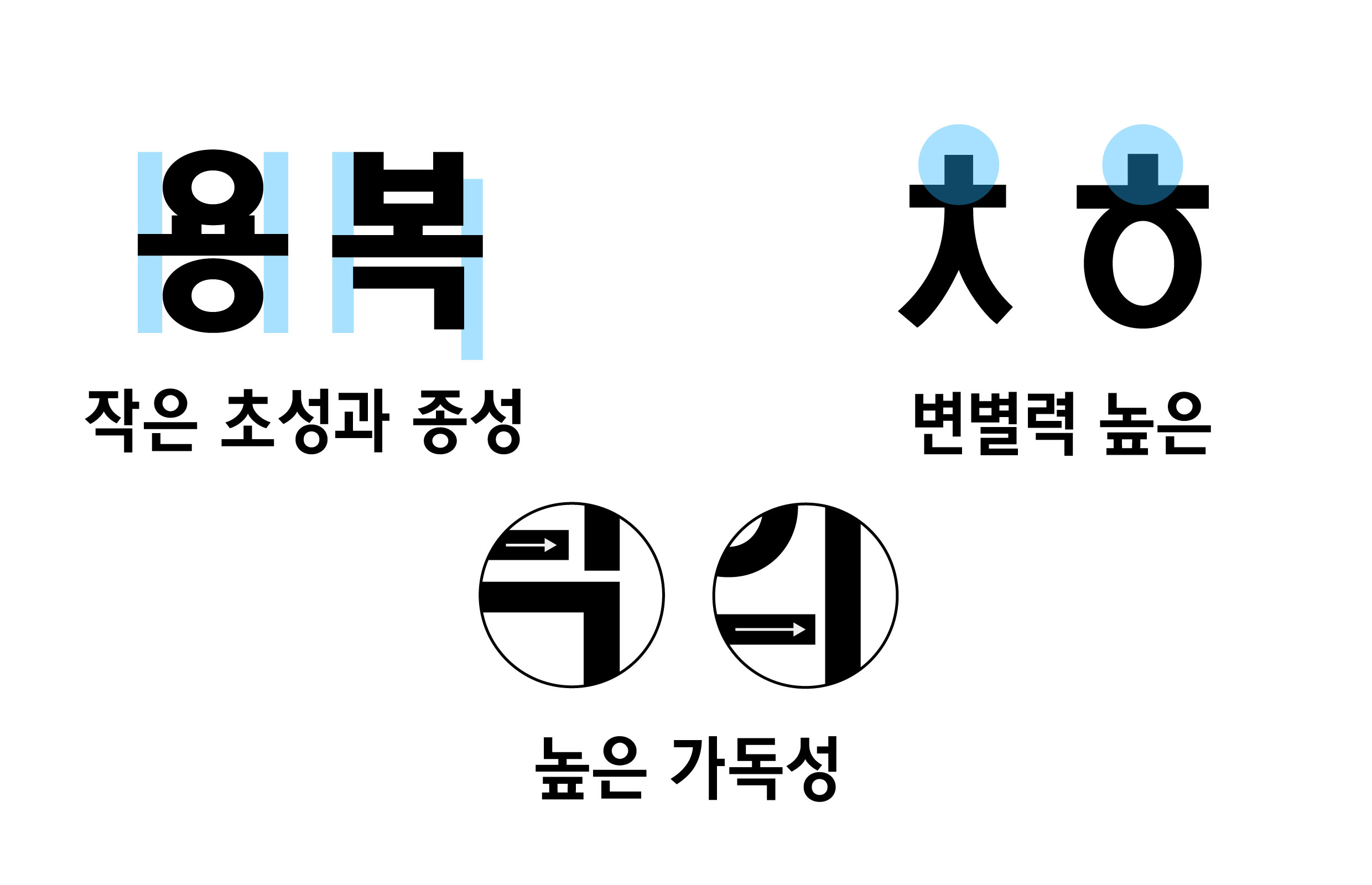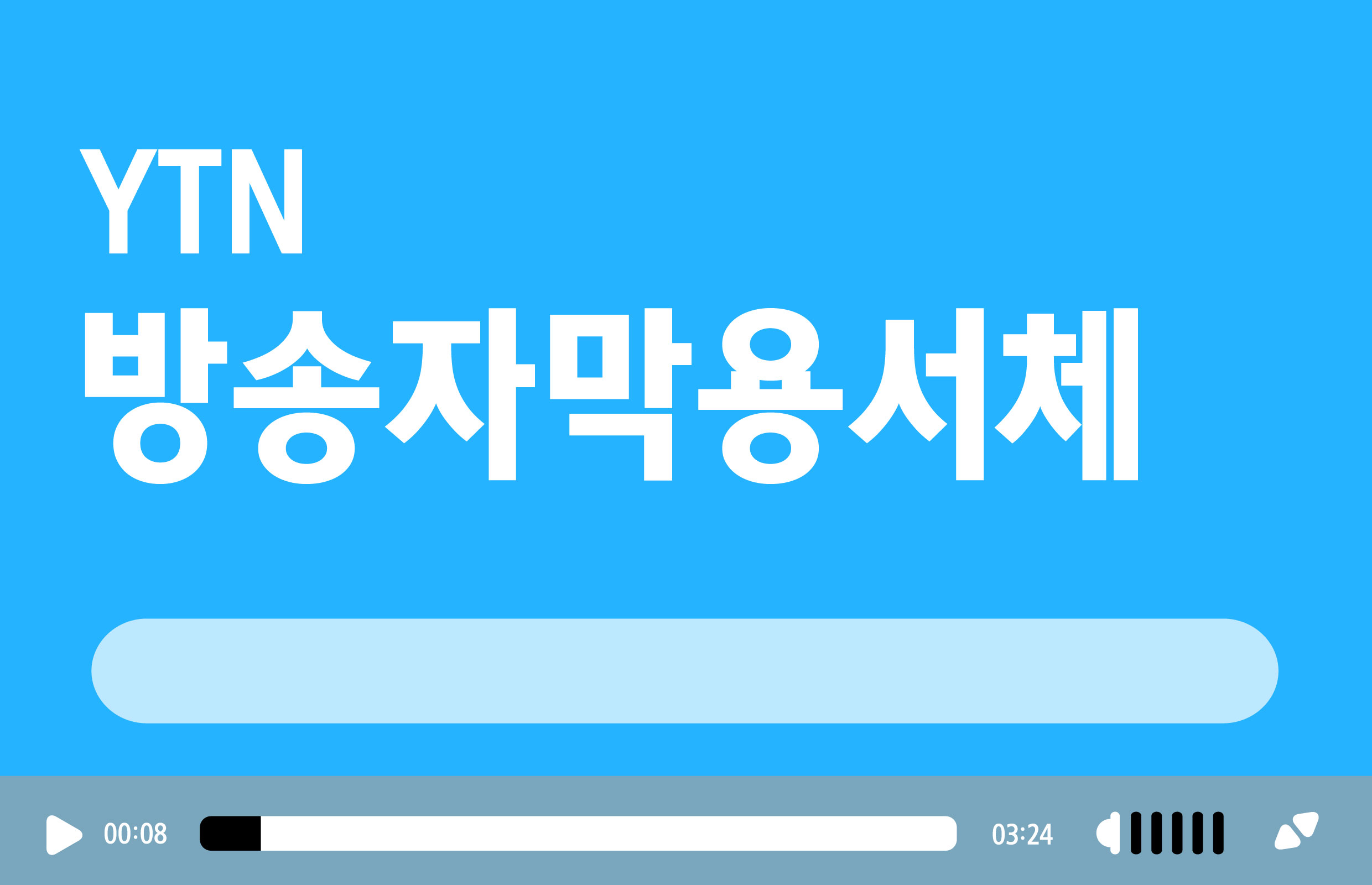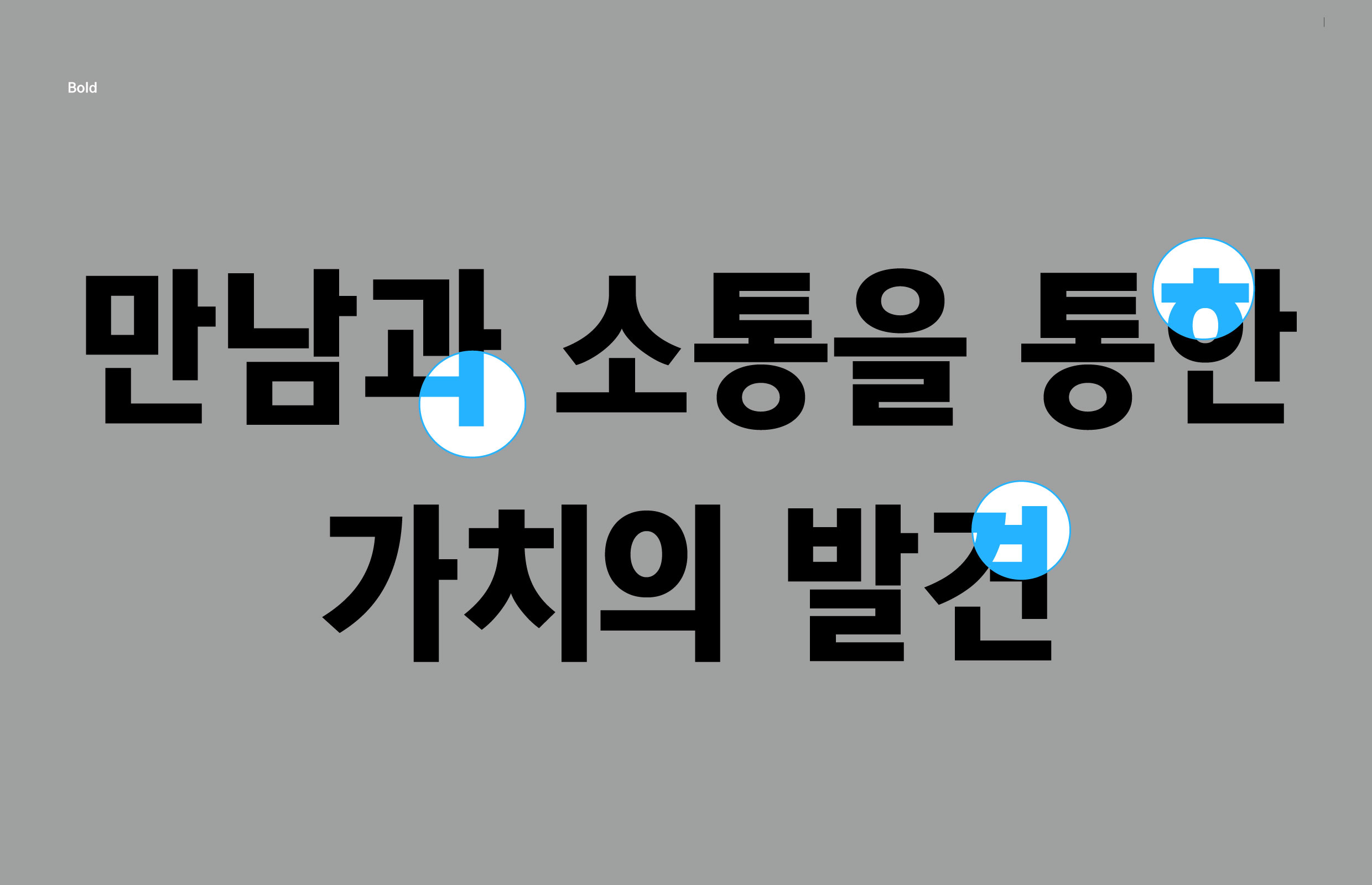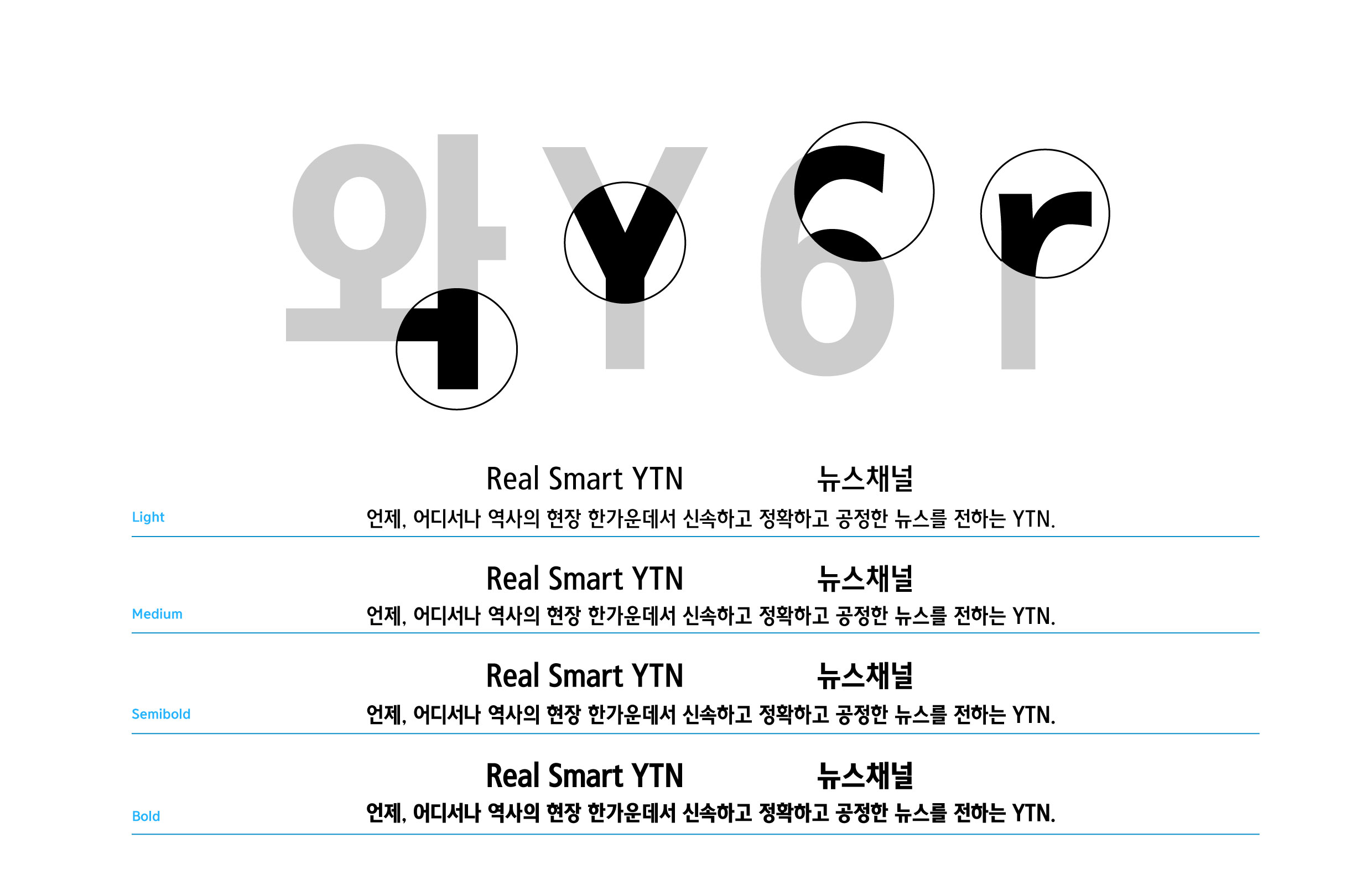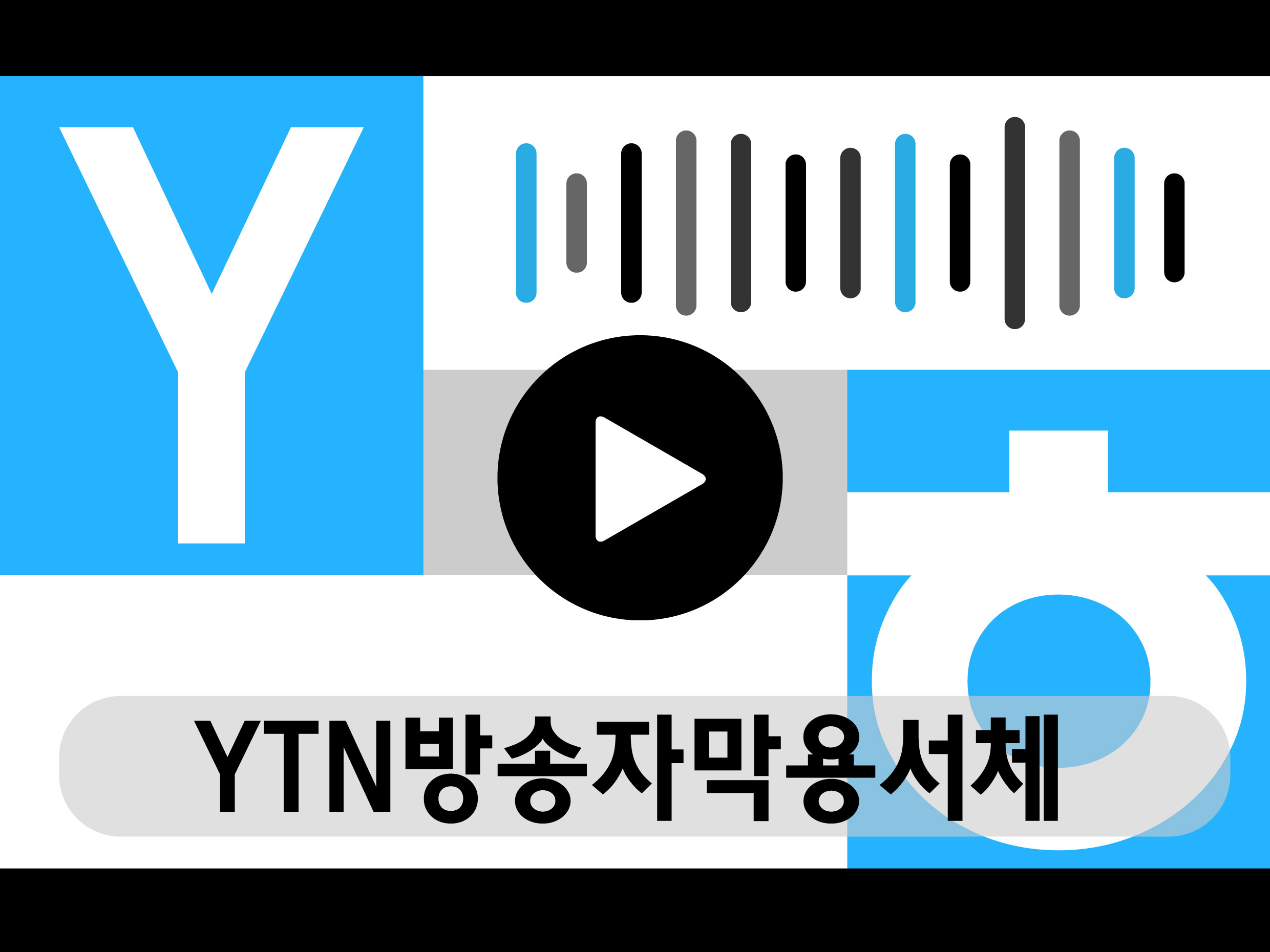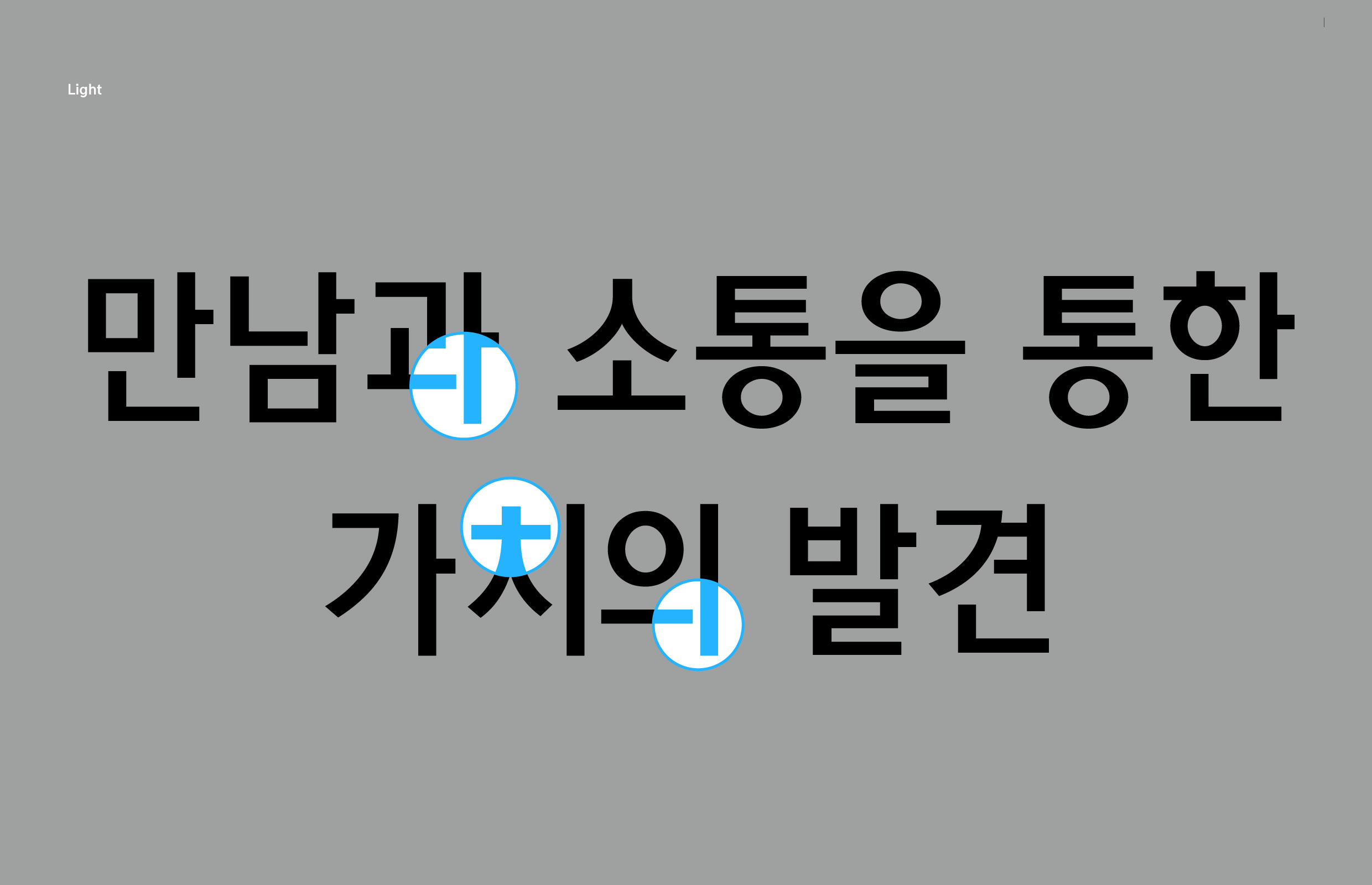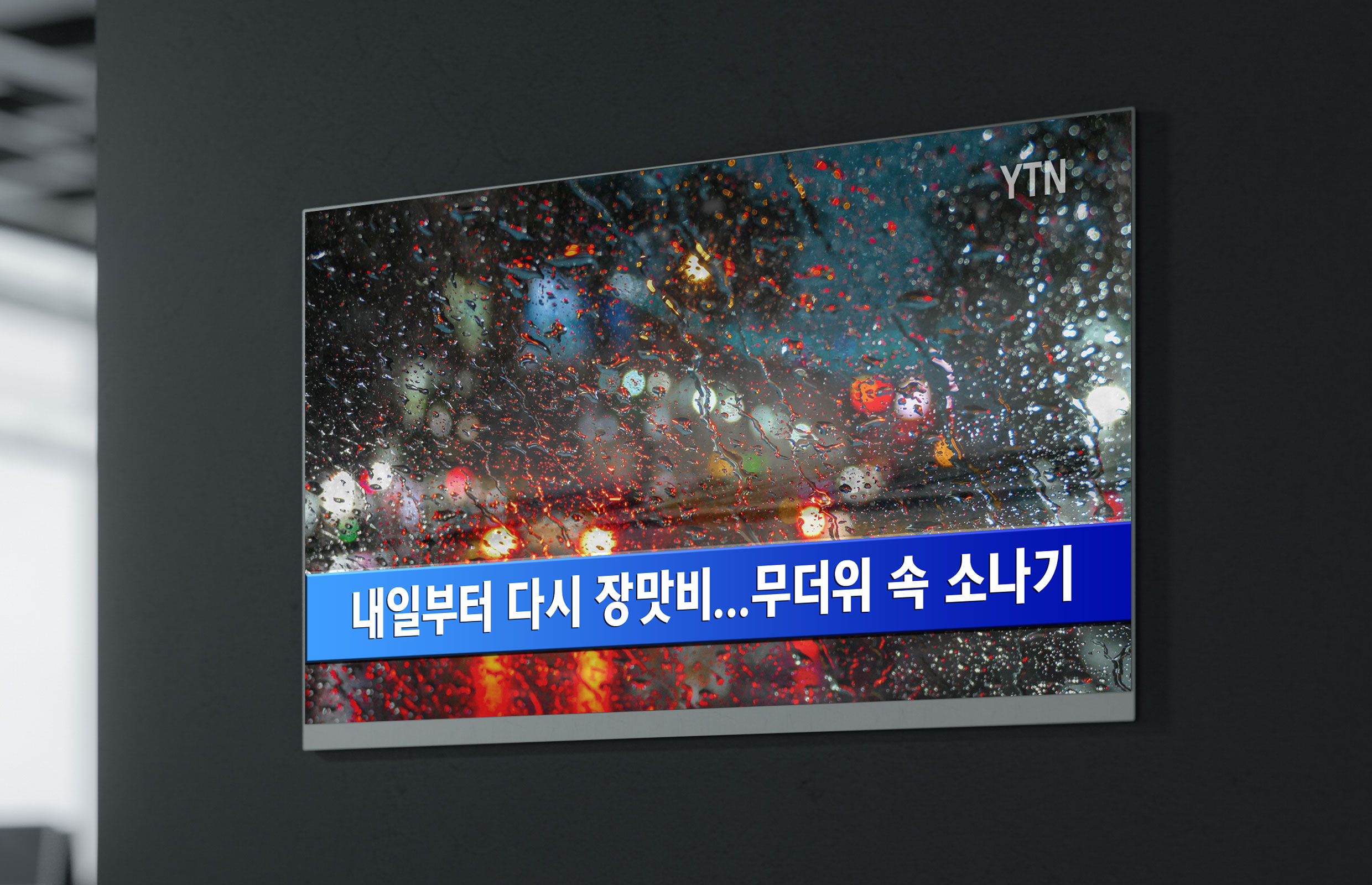
YTN
YTN [방송자막용서체]
고화질 모니터 환경에 적합한 방송 자막용 서체. 탈네모 구조, 직선으로 처리한 획 끝, 정원에 가까운 ‘ㅇ’꼴 등이 특징이다. 폰트 고유의 조형성을 해칠 수 있는 인위적인 장 설정을 지양하기 위해 기존 서체보다 15% 정도 가로 폭을 줄인 가변형 장체로 개발했다.